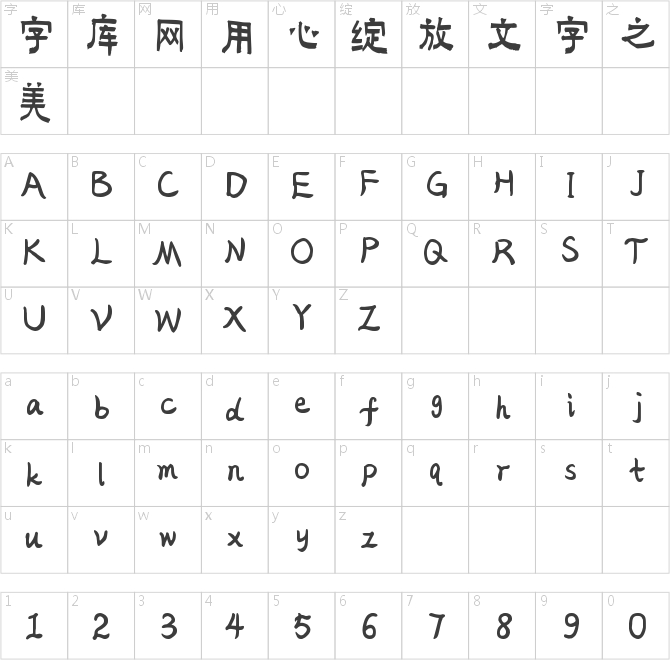
印品孔可立寶子體 詳情頁
印品孔可立寶子體通過一筆一畫的打磨,體現(xiàn)了寶子體的端莊、典雅、從容與細(xì)膩。而孔可立先生書法功力深厚,法度 嚴(yán)謹(jǐn),高古典雅,蒼利雋秀,動靜相生,形神兼?zhèn)?,個性鮮明,獨(dú)步一蹊及對文化傳承的決心,也在字體細(xì)節(jié)和氣質(zhì)神韻中得以彰顯。
印品孔可立寶子體字體字庫是一款讓人賞心悅目、百看不厭的中文字體,適合各類廣告和產(chǎn)品包裝設(shè)計(jì)應(yīng)用,字體大小5.76MB,格式為ttf字體,上傳用戶是Amanda白卉,作者/版權(quán)方為印品字庫